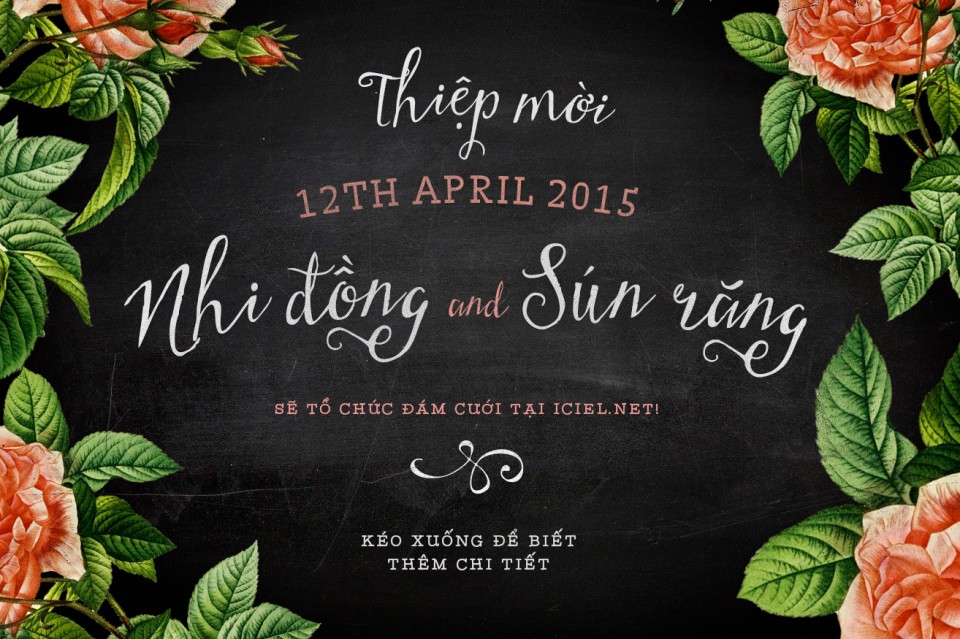
Tải Font việt hóa iCiel Stringfellows Miễn Phí Đẹp Nhất Cho Thiết Kế
Giới thiệu về bộ Font việt hóa iCiel Stringfellows
Trong thế giới đồ họa hiện đại, việc tìm kiếm một mẫu Font Chữ mang phong cách viết tay mềm mại nhưng vẫn giữ được nét sang trọng là điều vô cùng cần thiết. Font việt hóa iCiel Stringfellows chính là lựa chọn hoàn hảo cho các bạn học sinh và nhà thiết kế đang muốn tạo nên những tác phẩm nghệ thuật độc đáo. Đây là bộ font script nổi tiếng với những đường nét uốn lượn tinh tế, mang lại cảm giác thủ công tự nhiên và gần gũi. Khi được đội ngũ iCiel tiến hành Việt hóa, font đã được tối ưu hóa hoàn toàn để hiển thị các dấu tiếng Việt một cách chuẩn xác, không bị lỗi font khi gõ trên các phần mềm thiết kế phổ biến hiện nay.
Đặc điểm nổi bật của iCiel Stringfellows
Bộ Font việt hóa iCiel Stringfellows sở hữu cấu trúc các ký tự rất thanh thoát, phù hợp cho nhiều mục đích sử dụng khác nhau. Bạn có thể dùng font này để thiết kế thiệp mời, bìa sách, nhãn dán sản phẩm hoặc các dự án truyền thông trên mạng xã hội. Đặc biệt, với phong cách vintage cổ điển pha lẫn hiện đại, iCiel Stringfellows giúp nội dung của bạn trở nên nổi bật và thu hút thị giác hơn bao giờ hết. Khả năng tương thích tốt giúp người dùng dễ dàng cài đặt và sử dụng trên cả hệ điều hành Windows lẫn macOS.
Lợi ích khi sử dụng Font việt hóa iCiel Stringfellows
Sử dụng Font việt hóa iCiel Stringfellows không chỉ giúp tiết kiệm thời gian chỉnh sửa dấu mà còn nâng cao tính thẩm mỹ cho bản thiết kế. Thay vì dùng các font mặc định khô cứng, iCiel Stringfellows thổi hồn vào từng con chữ, giúp thông điệp truyền tải trở nên giàu cảm xúc hơn. Đối với các bạn học sinh, bộ font này cực kỳ hữu ích trong việc trình bày các bài thuyết trình hay thiết kế báo tường sinh động.